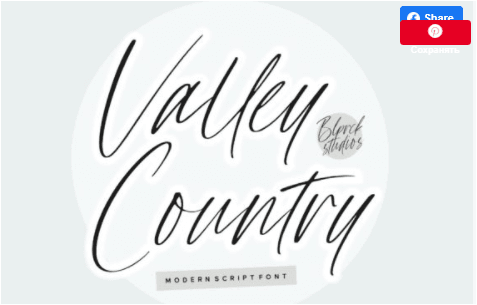
Valley Country Script Font
Valley Country Script — очаровательный рукописный шрифт. Этот универсальный рукописный шрифт имеет широкий спектр применений, от поздравительных открыток до заголовков, и гарантированно добавит романтическую атмосферу вашему следующему проекту.